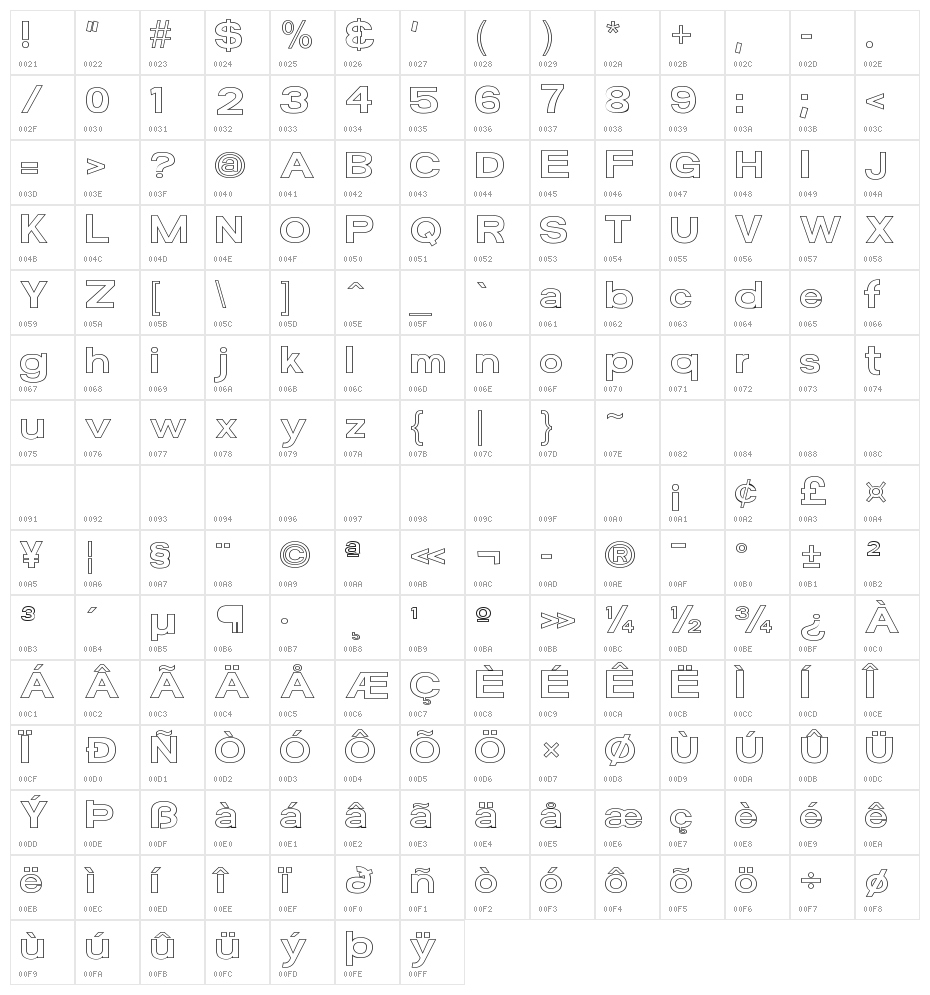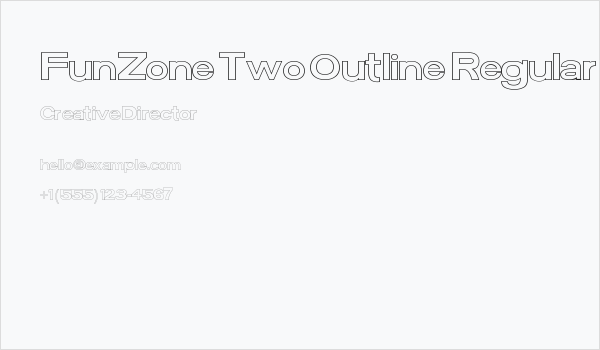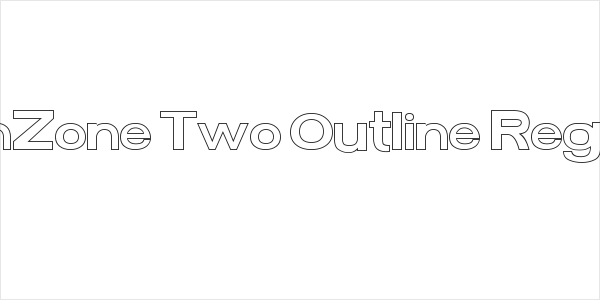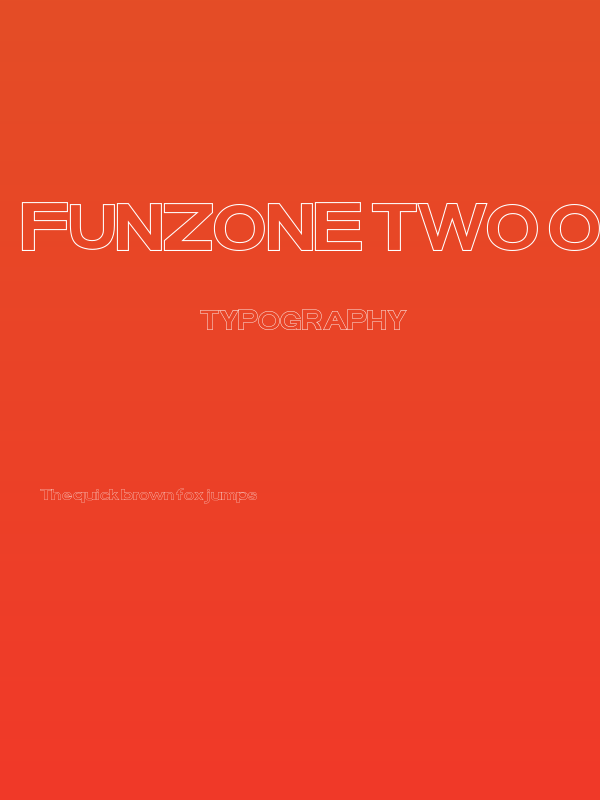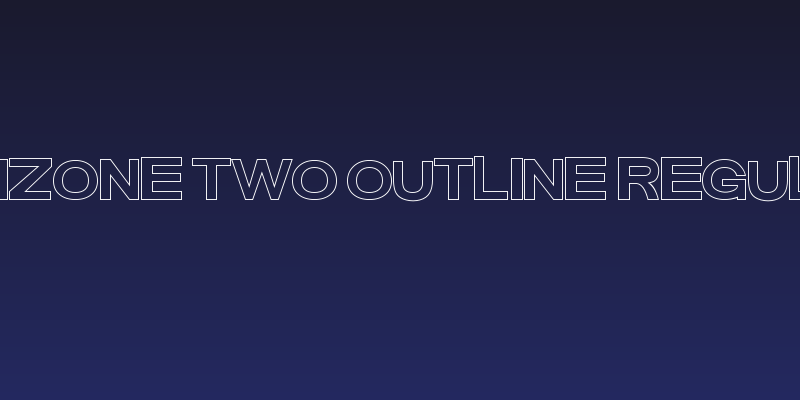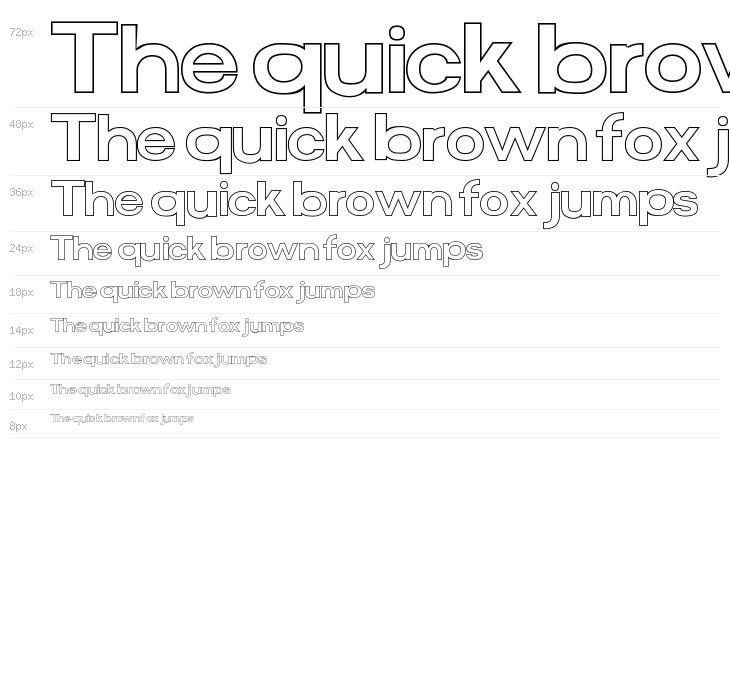
FunZone Two Outline Regular Font
| Progetti proposti | Ideal for creative projects such as posters, logos, and headlines where a modern and playful touch is desired. |